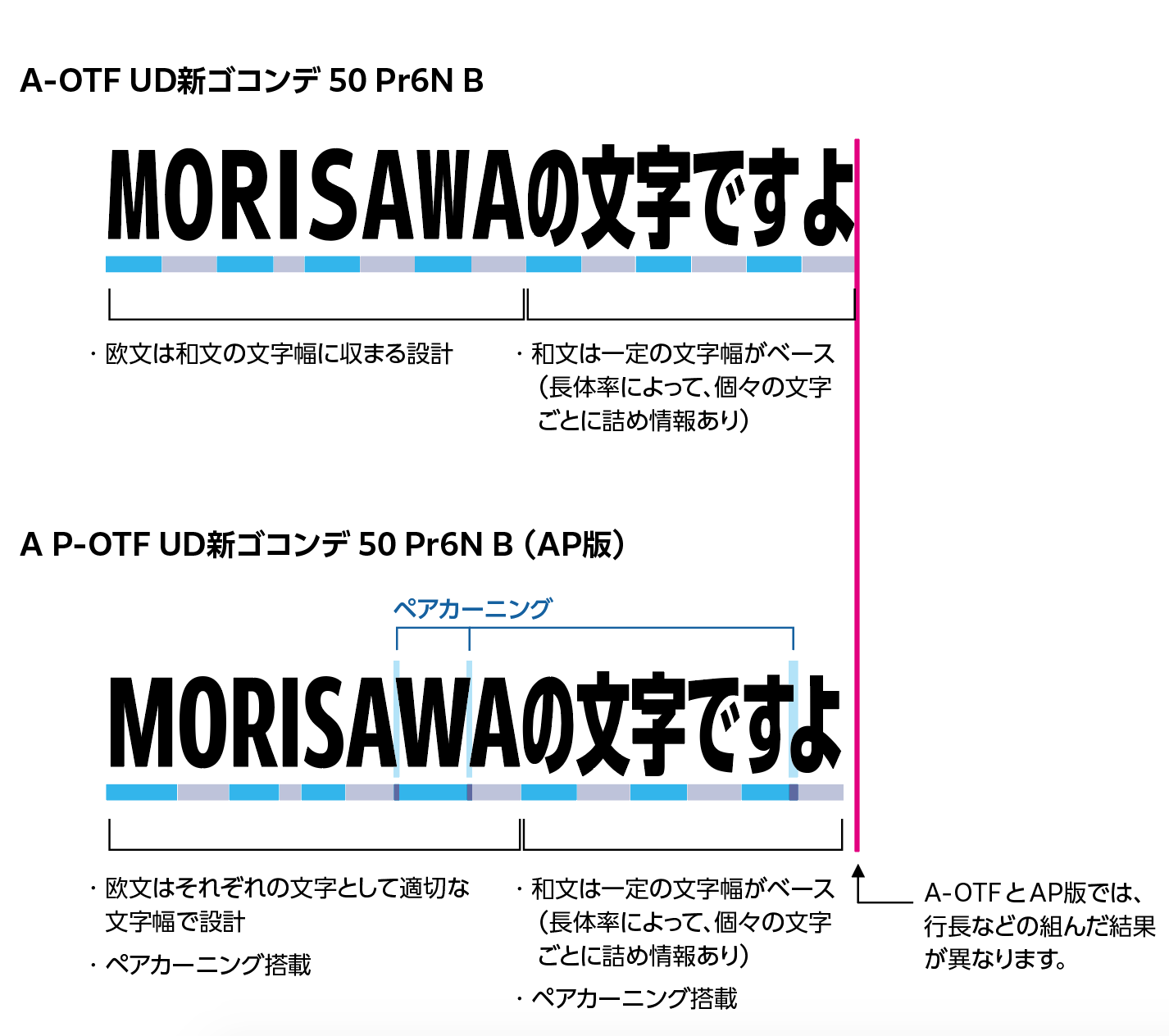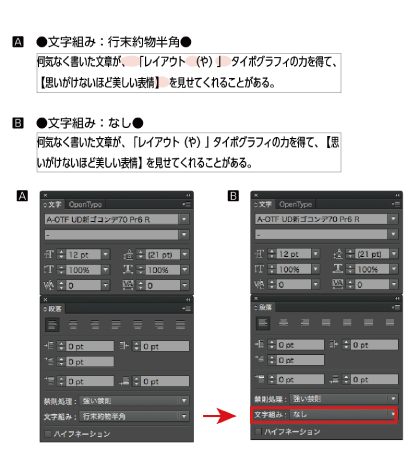
日本語のコンデンス書体には、アプリケーション側で変形をかけることで最適化されたデザインになるものと、仮想ボディそのものが正方形ではなく長方形でデザインされているためにアプリケーション側での変形を必要としないものがあります。
「UD新ゴ コンデンス」は後者のタイプに該当します。後者のメリットは、書体を変更するだけでその効果が得られることや、文字の変形を行うことができないアプリケーションでも、その効果を活用できることが挙げられます。
書体名に含まれる数字が変形の比率を表しています。
例)UD新ゴ コンデンス90:横幅が90%
※ 従属欧文は、漢字・かなに比べ圧縮率の変化が少ない設計です。
※ 縦組でのご利用は考慮されていません。
ベタ組の際の文字アキ
文字幅の取得方法や処理方法は、各アプリケーションによって異なります。約物などのアキ量をフォントの文字幅より取得・処理を行うアプリケーション以外では、フォントの文字幅を考慮しないアキ量で組版される場合があります。
文字組例
※ UD新ゴ コンデンス70 Pr6 R をAdobe Illustrator CCで組版した例。組版における調整方法
アプリケーションによって、機能・設定が異なります。 下記はAdobe Illustrator CCにおける設定の1例です。
「段落パレット」より、「文字組み」を「なし」に設定
A-OTFのフォントとAP版について
A-OTFのUD新ゴコンデンスと、AP版のUD新ゴコンデンスは、欧文のデザインや文字幅が異なります。
A-OTFのUD新ゴコンデンスは欧文を和文の文字幅に収まるようデザインしているのに対し、AP版のUD新ゴコンデンスは Clarimo UD PE Condensed がベースの欧文で、和文の文字幅にとらわれず欧文として適切な文字幅を保ちつつ、和文と欧文の組み合わせでもテンポよく読めるようデザインしています。
また、AP版のUD新ゴコンデンスはペアカーニング情報が搭載されています。
A-OTFのフォントとAP版での互換性はなく、置き換えると文字組の体裁が崩れたり、一部文字のデザインの変化が発生するため、置き換えは推奨しておりません。